Готичні шрифти історія, різновиди, інструменти для написання
Сьогодні хотів би розповісти вам про готичні шрифти. Пост довгий, але, сподіваюся, корисний для цікавляться каліграфією.
Ранній готичний шрифт (протоготіческій) - був широко поширений в західній Європі і використовувався з другої половини 11 століття до середини 13 століття, в період між кінцем каролингской епохи і початком готичної. Тому може розглядатися як перехід від каролингского Мінускул до текстурі, тому що поєднує в собі елементи з обох написаний.
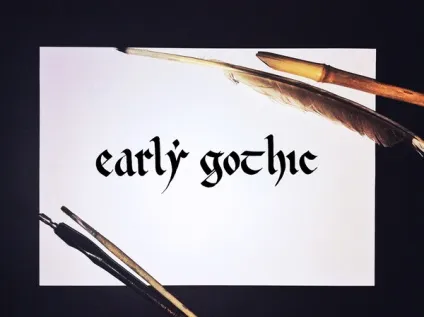
Тексту # x301; ра (від лат. Textura - тканину, також textura quadrata, Blackletter, Old English) - основний різновид готичного письма. словосполучення #xAB; готичний шрифт # xBB ;, як правило, асоціюється саме з цим варіантом. З'явилася на початку 13 століття. Свою назву текстура отримала за те, що покривала сторінку рівномірно. Характерна відмінність шрифтів даного типу - витягнутість букв. Шрифт був революційні зміни в каліграфії - після століть акценту на чітке розпізнавання письма, окремі літери були раптово підпорядковані загальному текстурних ефекту.
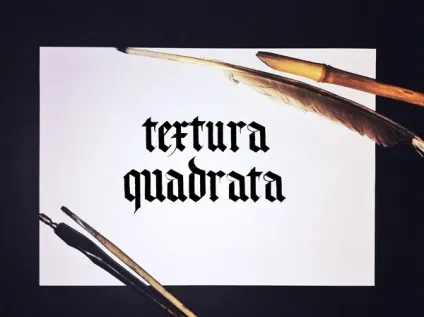
Textura Prescisus - розвивався паралельно з textura quadrata.Появілся імовірно на півдні Англії і поширився у Франції. До шрифту відноситься вираз vel sine pedibus (лат. #xAB; без ніг # xBB;), тому що відрізняється плоским квадратним підставою основного штриха.
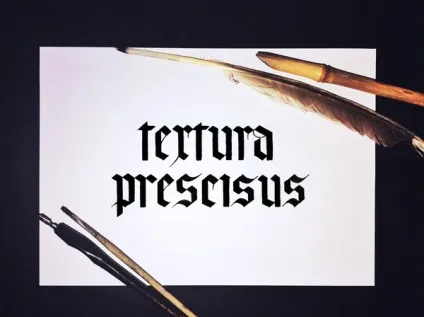
Bastard Secretary - чим більше формальним ставав манускріптний шрифт, тим більше була необхідність в більш функціональних шрифтах на додаток до них. Тому вишукані текстурні шрифти дали початок шрифтів для менш престижного, повсякденного листи. Кілька взаємодоповнюючих написаний розвивалися як на регіональному, так і на національному рівні, швидко перетворюючись в повноцінні шрифти. І класифікувалися вони як #xAB; гібридні # xBB; (Bastarda), термін, що позначає шрифти змішаного скорописного і текстурного походження.
Подібне явище, імовірно, взяло початок в кінці 12 століття, для оформлення документів.
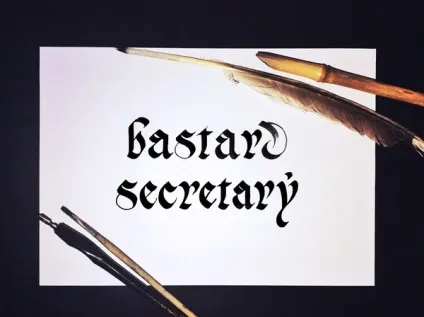
Batarde (Lettre Bourguignonne) - французький еквівалент англійського Bastard Secretary. Був розроблений в кінці 13 століття і використовувався аж до середини 16, розвинувся з скорописного в повноцінний формальний шрифт. Досяг своєї найскладнішої форми в середині 15 століття, в епоху, коли популярність друкованих книг все більше зростала серед широких верств населення. У такій формі був поважаємо в Бургундських придворних колах, звідки і друга назва.
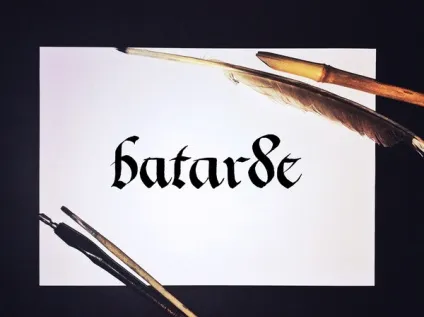
Фрахт # x301; ра (нім. Fraktur - надлом, German letter) - пізня різновид готичного письма, перші рукописні приклади датуються приблизно 15 століттям, друкована версія з'явилася століттям пізніше. Являє собою суміш німецької скоропису і текстури. Ранні варіанти з'явилися як народні, загальновживані написання, і пізніше були взяті за основу для багатьох друкованих шрифтів.
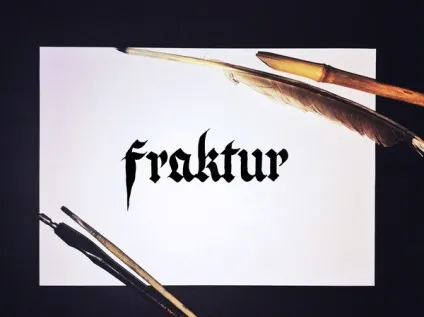
Швабахер, швабах (нім. Schwabacher) - різновид готичного письма, зародилася в 15 столітті. Ламане лист з округленими обрисами деяких букв. Цей шрифт домінував в Німеччині з кінця 15 до середини 16 століття. Після чого був замінений на фрактура, але залишався популярним до 20 століття. Схожий на текстуру, але більш округлу, просту версію.
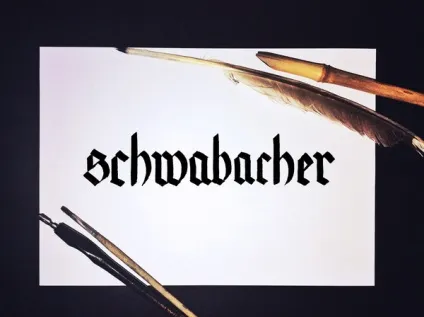
Роту # x301; нда (італ. Rotonda - кругла) - італійський варіант готичного письма (полуготіческій шрифт), що з'явився в XII столітті. Відрізняється округлено і відсутністю надлому. Отримав початок від каролингского Мінускул. Готичне вплив на написання східної Європи між 10 і 13 століттями отримало сильний опір в Італії. Чіткі форми класичних написаний, використання каролингского Мінускул сприяли появі шрифту, що відрізняється від готичного більш круглими, відкритими формами і короткими виносними елементами. Був поширений аж до 18 століття, в тому числі набув широкого поширення в Іспанії.
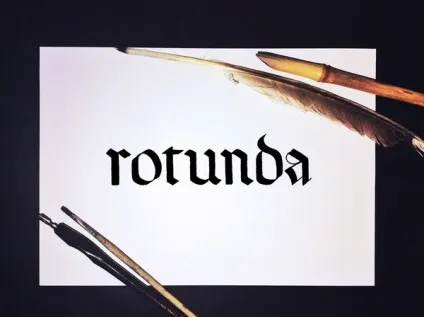
Тепер про інструменти. Всі вищеописані почерки історично писалися за допомогою пташиного пір'я. Сьогодні ж можна застосовувати практично будь-який інструмент або предмет з плоским широким закінченням. Наведу кілька прикладів.
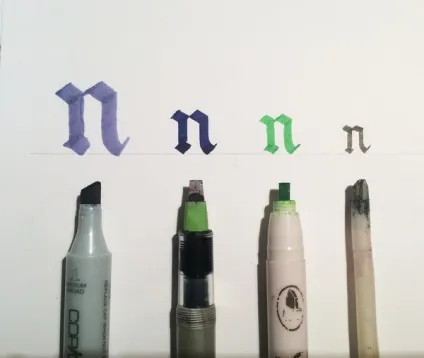
Далі зліва направо:
- маркер Copic з плоским наконечником;
- ручка Pilot Parallel Pen;
- двосторонній каліграфічний маркер фірми Marvy;
- пташине перо;
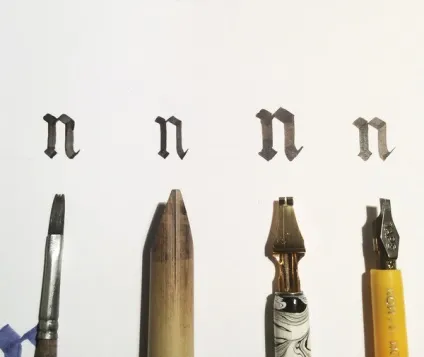
- кисть синтетика;
- очеретяна паличка (калам);
- шірококонечное плакатне перо;
- шірококонечное перо з правим скосом;
- китайська паличка для їжі з плоским закінченням;
- зубочистки, скріплені з олівцем;
- каліграфічний маркер фірми ZIG Kuretake;
- два олівця, пов'язані гумкою.